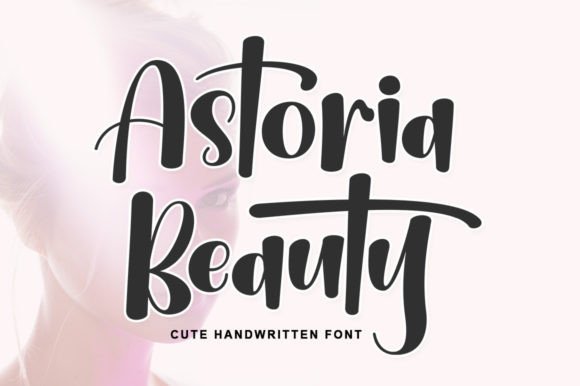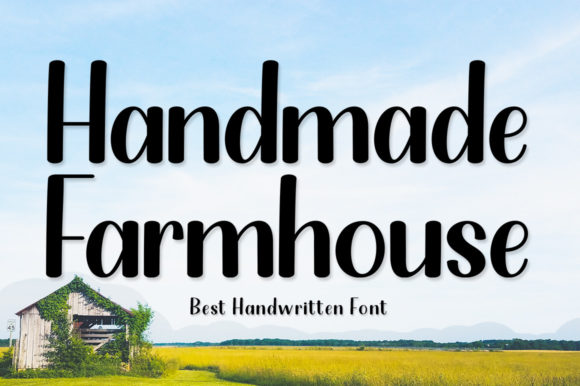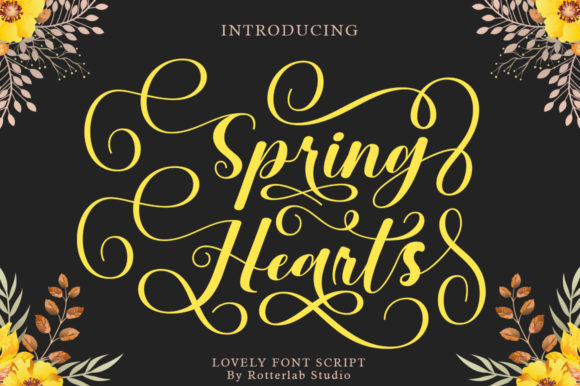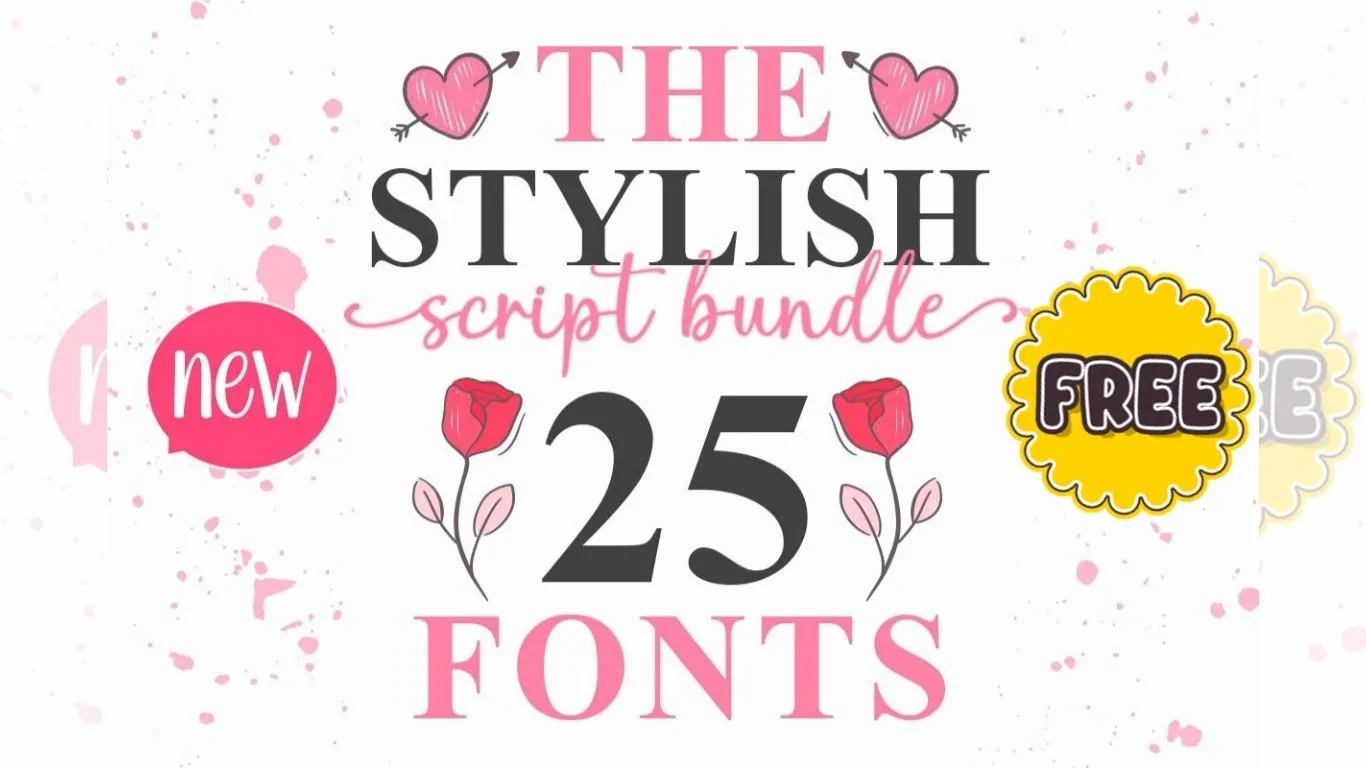
Creative Fabrica 免費字體包 The Stylish Script Bundle
字體包裡有什麼?
由設計師 rotterlabstudio 製作的字體合集,共收錄 25 款英文草書與手寫字體。這些字體設計幾具個性,適合用於婚禮請柬、品牌、手作卡片、社群媒體貼文,以及各類 DIY 創意專案。以下列舉部分收錄字體:
優雅浪漫 (Astoria Beauty、Amoreta)
農村鄉村風 (Handmade Farmhouse、Simple Country)
清新甜美 (Spring Hearts、Snowlove) 等